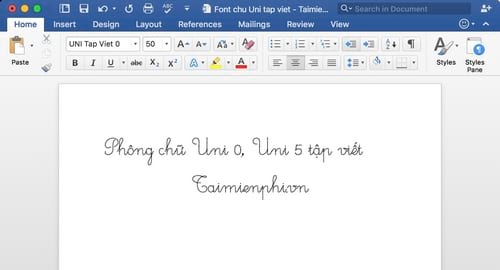
Font Uni tập viết gồm hai dạng font có kẻ ô ly và không kẻ ô ly thích hợp cho học sinh tiểu học rèn luyện mặt chữ, cách viết chữ đẹp. Nếu bạn là người không có thời gian để ra hiệu sách mua quyển tập viết hay muốn tự tạo những cách rèn luyện chữ viết riêng cho học sinh, con em của mình thì hãy cài Font Unitapviet 0 và Uni tập viết 5 cho Macbook